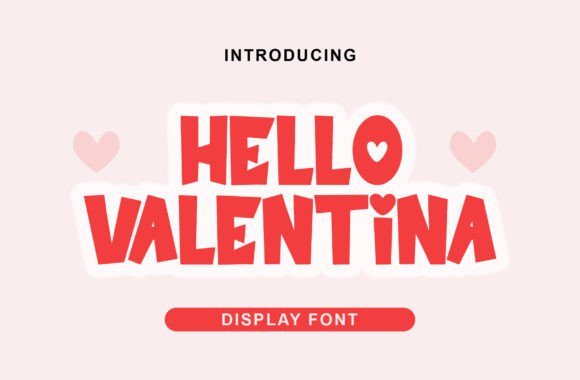
Hello Valentina
إذا كنت تبحث عن أصول عالية الجودة مثل Hello Valentina، فإن هذه الحزمة المميزة هي خيار رائع لمشاريعك الإبداعية.
سواء كنت تقوم بإنشاء منتجات الطباعة عند الطلب أو دعوات الزفاف أو رسومات وسائل التواصل الاجتماعي، فإن Hello Valentina هو الخيار المثالي.